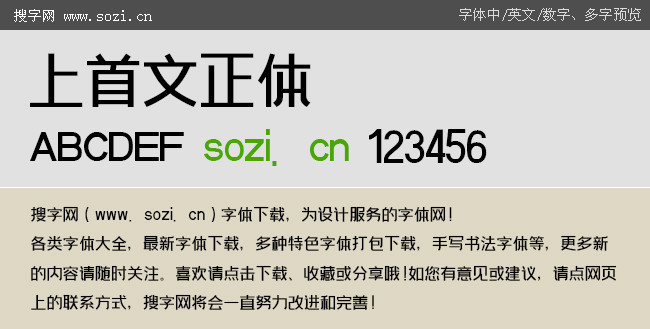
上首文正體
搜字網(wǎng)給大家提供一款上首文正體中文字體下載,上首文正體結(jié)構(gòu)方正,線條流暢,簡(jiǎn)化字體筆畫中的“鉤”,轉(zhuǎn)角做圓化處理,為此套字體亮點(diǎn),橫豎筆畫大小統(tǒng)一,嚴(yán)謹(jǐn)、有力,適用于搭配標(biāo)志、廣告標(biāo)語(yǔ)、商業(yè)廣告等。